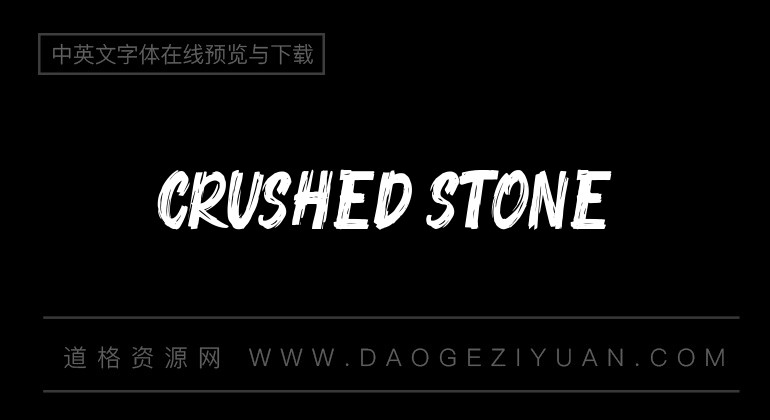
Crushed Stone
Crushed Stone 字体是一款由 Oceana Studio 创作的粗体字体,它可以用来制作报纸标题、海报、海报、品牌标识等。它的特点是具有粗犷、粗糙、粗暴的外观,体现出古老的石头砌筑的外观,能够为您的设计带来一种独特的外观。它的字体结构也很独特,具有特殊的视觉效果,能够搭配多种不同的背景,让您的设计更加醒目。
Crushed Stone是一款非常不错的手写艺术字体,具有很好的视觉感,适合于文化类的宣传设计、商业类品牌的广告和产品包装设计以及个性化文字排版等较多场景。